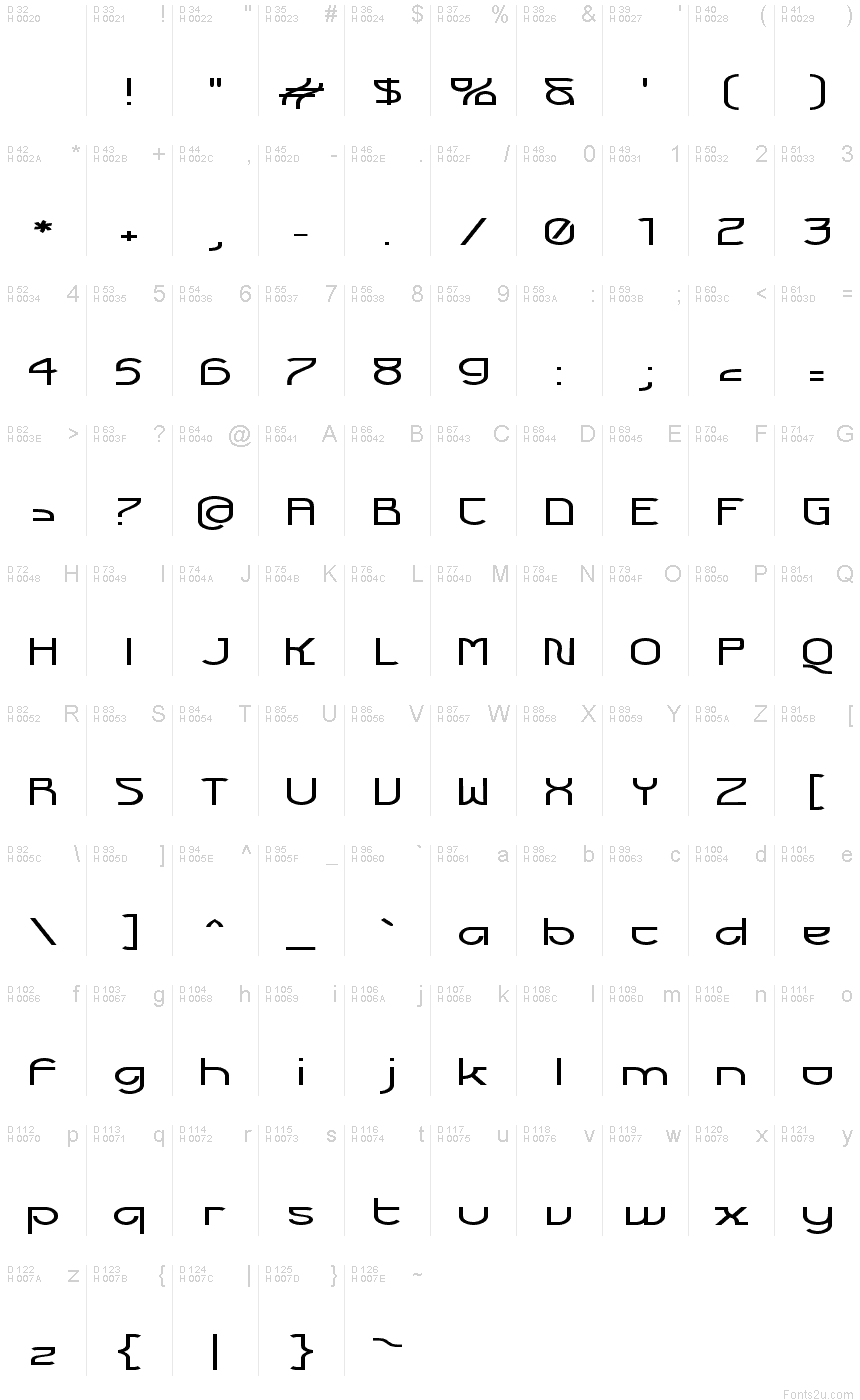
Futurex Voyager von Rich Gast ist eine kostenlose, futuristische Display-Schrift, die wirkt, als käme sie direkt von der Konsole eines Raumschiffs. Lange, geschwungene Linien und enge, quadratische Innenräume verleihen ihr ein schnittiges, technisches Design. Die niedrigen, gestreckten Formen lassen den Text horizontal gleiten – wie eine leuchtende HUD-Anzeige. Sie wirkt glatt und präzise, mit genau der richtigen Kante, um fortschrittliche Technologie und Sci-Fi-Welten zu evozieren.
Mit Futurex Voyager erhalten Titel und Wortmarken für Sci-Fi-Poster, Indie-Games, Tech-Startups, UI-Mockups, Event-Branding und Streaming-Overlays sofort einen „Next Century“-Look. Diese kostenlose Schrift glänzt besonders in großen Größen, wo ihr gestreckter Rhythmus richtig atmen kann; kombinieren Sie sie mit einer schlichten, geometrischen serifenlosen Schrift für den Fließtext, während Futurex Voyager die dramatischen, futuristischen Überschriften übernimmt.
Futurex Voyager
My contribution to the Futurex Project of Graham Meade and Apostrophe.